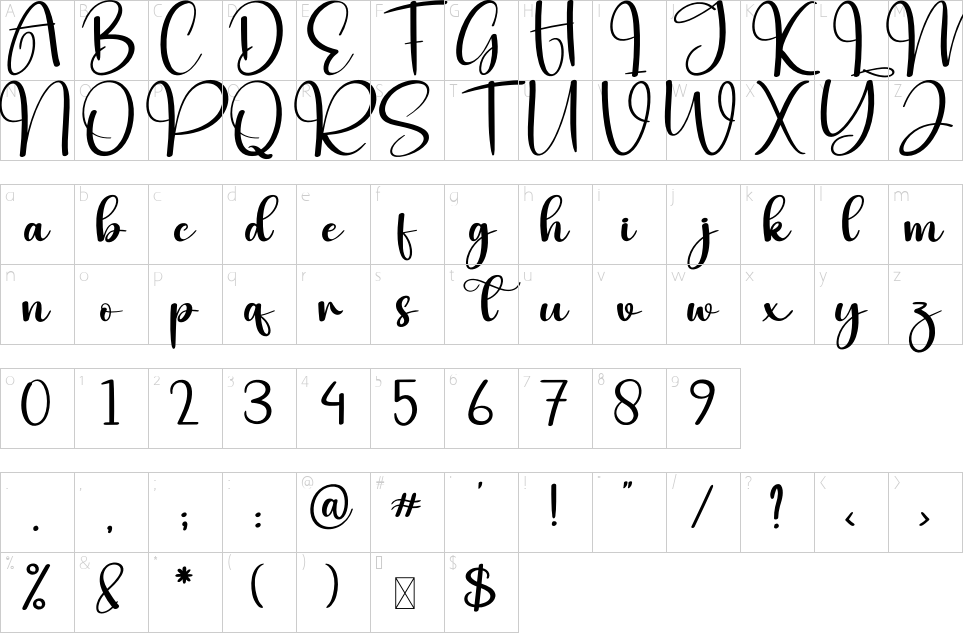
A Magistica Font oferece um estilo elegante e minimalista, perfeito para projetos de design gráfico. Seu design limpo e harmonioso combina bem em diversas aplicações, seja em aplicativos de desktop Windows e Mac, ou em projetos digitais de nível profissional. Com o design cuidadoso de scratchones, essa fonte gratuita é uma excelente opção para quem procura um estilo moderno e versátil. Desde o design de sites até o layout de e-mail, a Magistica Font traz um toque diferenciado e elegante sem custos adicionais. Com apenas 483 downloads, provamos que a beleza e o design atingem um alto nível, mesmo em um ambiente de fontes gratuitas. Descubra por si mesmo o poder de uma fonte que não apenas faz sua marca mais visualmente atraente, mas também expressa seu estilo de maneira única.